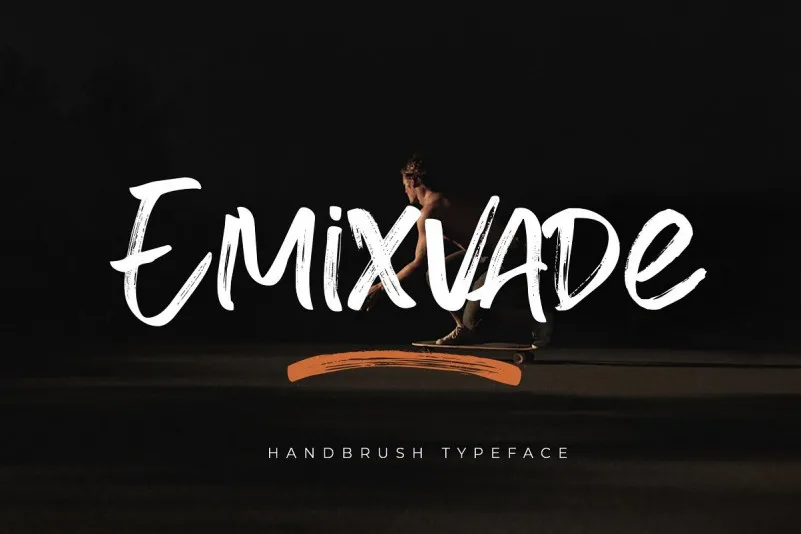
Emixvade Brush Font – Download Grátis
Estou aqui uma descrição envolvente para a página de download da font “Emixvade Brush”, ideal para a categoria de Script Fonts: Agradecemos por prestigiar a Emixvade Font, uma seleção cuidadosamente concebida para quem valoriza um estilo autêntico e confiante. Esta é uma fonte script que reflete a natureza humana através da escrita manuscrita, com suas ondulações naturais e personalidade única. A Emixvade Brush foi criada com técnicas meticulosamente desenvolvidas, usando um canivete para garrafas de tinta. O resultado é uma fonte que transmite a elegância do estilo autêntico, pronta para destacar em sua próxima criação gráfica. Esta seleção de recursos é ideal tanto para os projetos de assinatura e logotipos como para o desenvolvimento de materiais publicitários ou embalagens – todas com um toque único que irá agradar seus leitores. A Emixvade Brush também se destaca por sua versatilidade, permitindo aplicação em texturas interessantes e títulos de pôsteres. Uma vez instalada na sua máquina de edição de texto ou design gráfico favorita, esta fonte irá complementar seu trabalho como nenhum outro. Como uma fonte Script com estilo autêntico, a Emixvade Brush é perfeita para projetos em que você deseja transmitir confiança e personalidade através do uso da sua escrita. Seja para os títulos de página ou as partes mais importantes das suas criações gráficas, esta fonte oferece uma solução elegante e inovadora. A Emixvade Brush é perfeita para quem busca aperfeiçoar o seu design com um toque único – seja você designer gráfico profissional ou pessoa que simplesmente adora criar designs de qualidade.